Familia Lafuente, detrás de la «Compañía Vascongada» en Santander
Quizás sea uno de los rótulos más característicos de Santander. Ubicado en una de las paredes de la calle comercial por excelencia, la calle San Francisco, se encuentra el rótulo de la Compañía Vascongada.
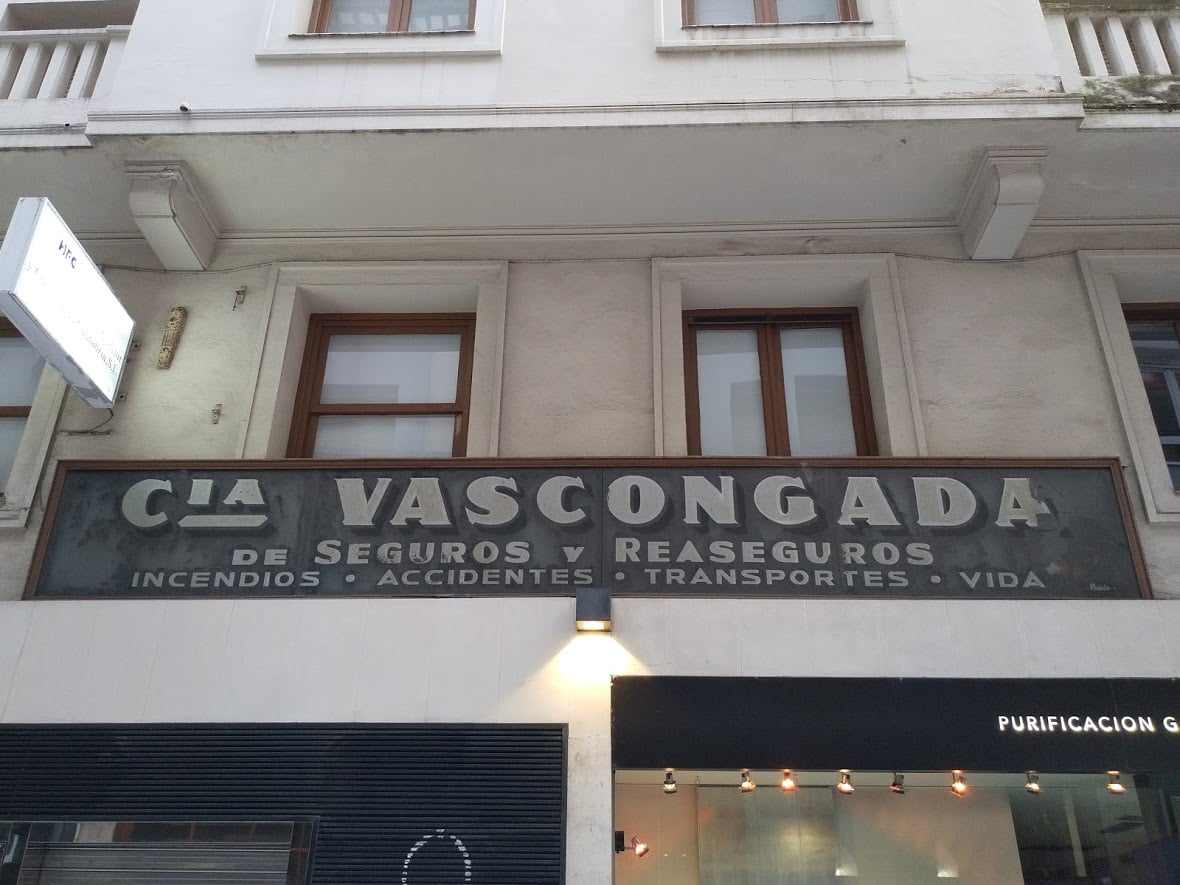
El rótulo hoy (Santatipo, 2020).
Este rótulo, que probablemente se salvó del incendio de 1941 (hace ya 80 años) que asoló todo el casco histórico de Santander, convirtiéndola posteriormente en la ciudad que conocemos. Fue colocado ahí por iniciativa popular, y hoy día podemos seguir disfrutando de esa tipografía y lo que nos cuenta.
Pero, siempre hubo alguna incógnita al respecto, dado que se desconoce quién estaba detrás. Y hoy, gracias a las Redes Sociales, se ha podido abrir una pequeña puerta. La casualidad ha querido que una descendiente de estos contactase con Santatipo. Olga Blasco, es nieta de quien abrió esta surcursal en Santander, Manuel de Lafuente.
Lafuente
Además Manuel no sólo tuvo esta sucursal de Seguros, también estuvo detrás del concesionario SEAT Lafuente en los años setenta, y tuvo una Escuela de Vela «Naútica Lafuente» en el hoy Puerto Deportivo de Santander. Esta actividad empresarial, vinculada al apellido y la ciudad, viene de la tradición familiar.
Su padre Joaquín Lafuente, a comienzos del siglo XX, tuvo en origen en la antigua calle Blanca una Sastrería «Lafuente y Rodriguez» para posteriormente ubicarse en la calle San Francisco con la ya «Sastrería Lafuente«. De momento esta poca información, es un gran paso paso para descubrir a esta familia e investigar en esta amplia actividad comercial.
Sastrería Lafuente y Rodriguez, en la calle Blanca. Arriba se puede ver el rótulo con la tipo pintada en la madera. ca.1918 (Autor desconocido)
Interior Sastrería Lafuente, en la calle San Francisco; ca. 1924 (Archivo familiar Olga Blasco)
Joaquin Lafuente en el centro; ca. 1930 (Archivo familiar Olga Blasco)
Factura Sastrería Lafuente y Rodriguez; 1918 (Santatipo)
Factura Sastrería Lafuente; 1923 (todocolección)
Publicidad de “España en la mano”: Anuario ilustrado de la riqueza industrial y artística de la Nación; 1927 (todocoleccion)
Publicidad en el reverso de un Disco de Control de estacionamiento en zona azul; años 70 (Santatipo)
Publicidad de la Escuela Náutica LaFuente; fecha desconocida pero probablemente estemos en los años 80. (Archivo familiar Olga Blasco)